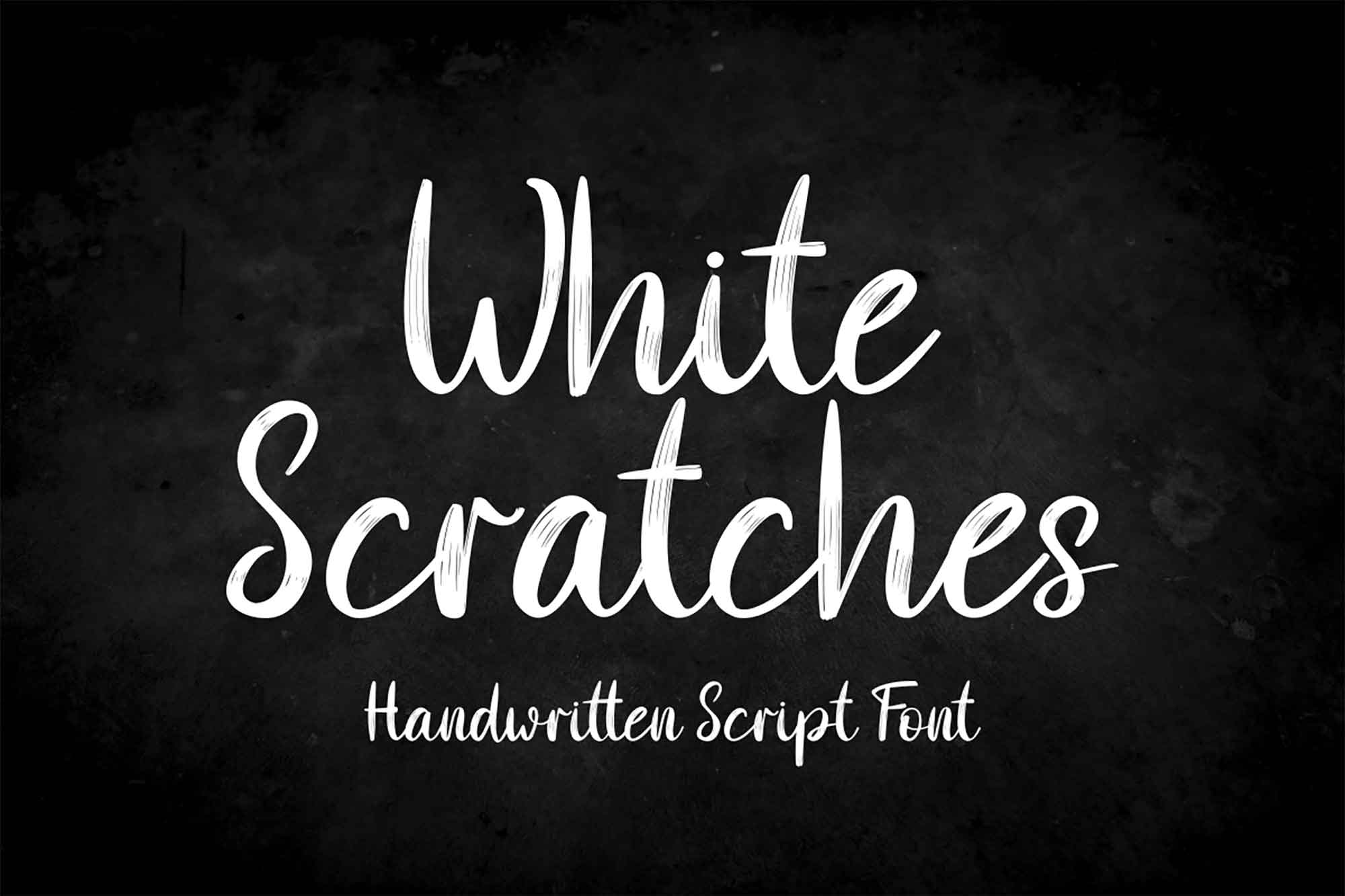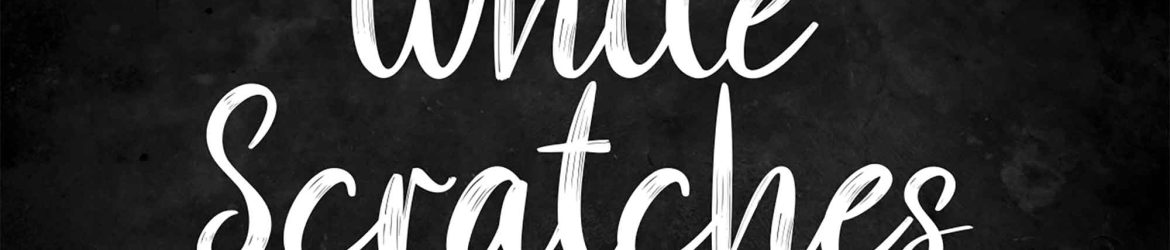
A fonte ‘White Scratches’ é uma tipografia escrita à mão com um estilo casual e amigável, adicionando um toque descontraído a qualquer projeto. Perfeita tanto para headlines, títulos e subtítulos quanto para combinar elegante com outras tipografias formais. Esta fonte é ideal para quem busca um toque único e autêntico sem perder o respeito e a elegância. Seja para aplicativos de redes sociais ou sites, White Scratches enriquecerá seu layout de forma profissional, deixando um impacto visual atraente e distintivo. Com a flexibilidade para personalizar textos e gráficos, este recurso gráfico é uma ótima opção para designers, especialmente aqueles buscando adicionar um toque de personalidade sem comprometer a estética formal.